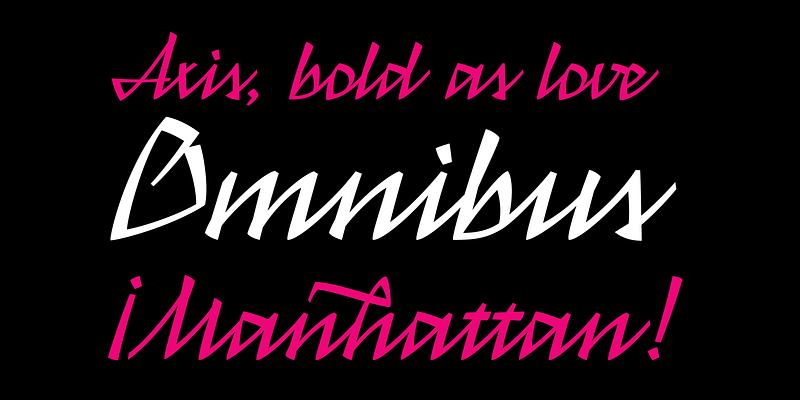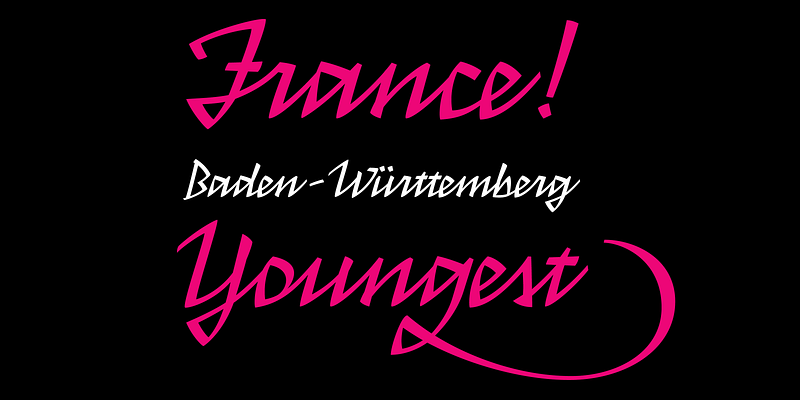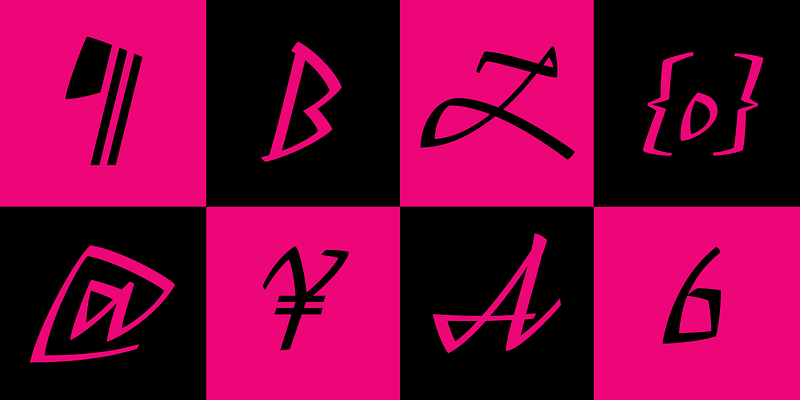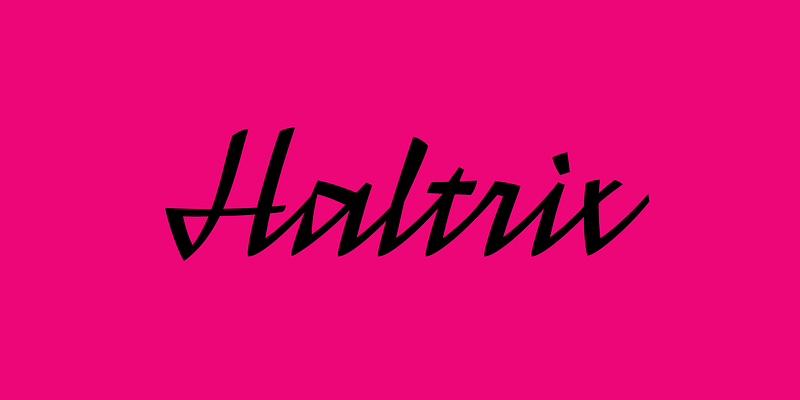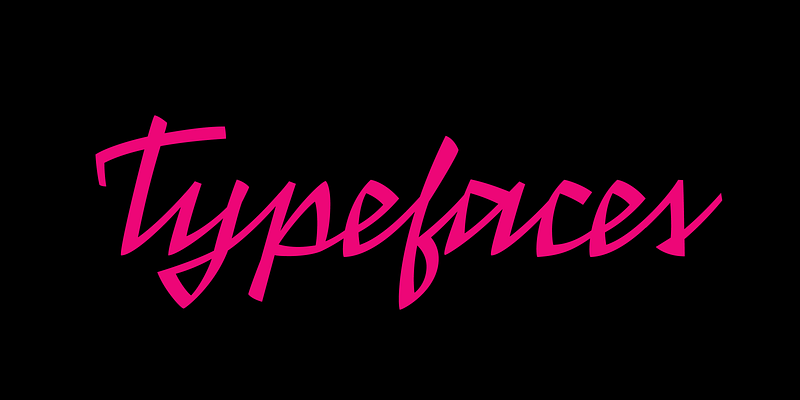
Grundsätzlich bestehen die meisten Schreibschriften aus Elementen wie glatten Schwüngen und zarten Bogen. Das Konzept von Haltrix geht in die entgegengesetzte Richtung, wobei die Handschrift des Designers der Ausgangspunkt war. Bei der Ausgestaltung wurde immer versucht, die Buchstaben möglichst aggressiv und eckig aussehen zu lassen, indem Kurven vermieden und gerade Liniensegmente betont wurden. Haltrix reiht sich in andere Schreibschriften wie Arcana von Gabriel Martínez Meave und die fantastische Mistral von Roger Excoffon (sowie deren Hommage, die Nouvelle Vague von Elena Albertoni) ein. Auch wurde die Schrift von Frakturen beeinflusst, sodass sie einen kantigeren Ansatz verfolgt als ihre Vorgänger. Bei der Schriftart handelt es sich um eine verbundene Schrift, die auf der OpenType-Kontextvariantenauswahl beruht und verschiedene Alternativen, Zierbuchstaben und eine umfassende Sprachunterstützung bietet.